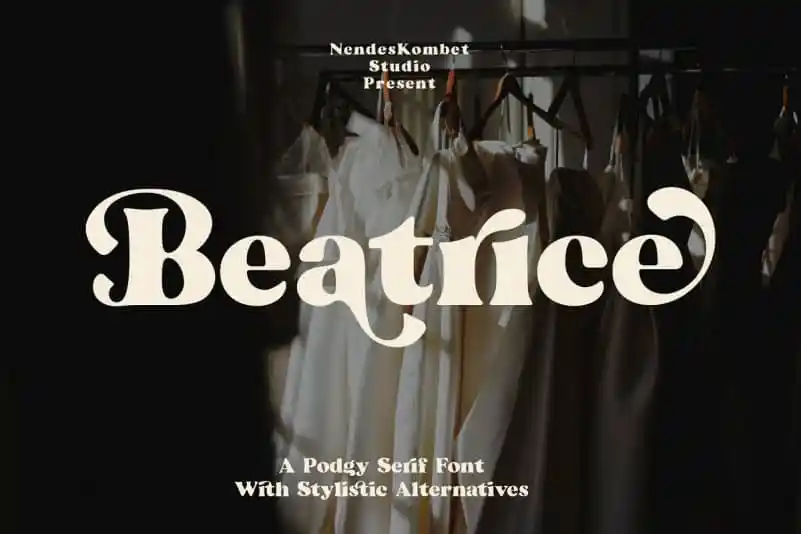
A Beatrice Serif Font é uma nova adição para colecionadores de serifas, criada especialmente pelo designer NendesKombet na plataforma 99designs. Esta fonte traz a essência dos estilos antigos dos anúncios e letras escritas à mão, misturando-a com um toque moderno que a torna única. Com seu vasto conjunto de alternativas estilísticas, é uma escolha perfeita para aplicar em diversos projetos gráficos como headlines, logotipos, postais, embalagens e até mesmo camisetas. Sua aparência contemporânea permite-lhe se adaptar a uma variedade de temas, garantindo que sempre fique na moda sem perder seu carácter clássico. Composta por linhas finas e espessas, esta fonte é perfeita para criar um design vibrante e moderno no seu próximo projeto.